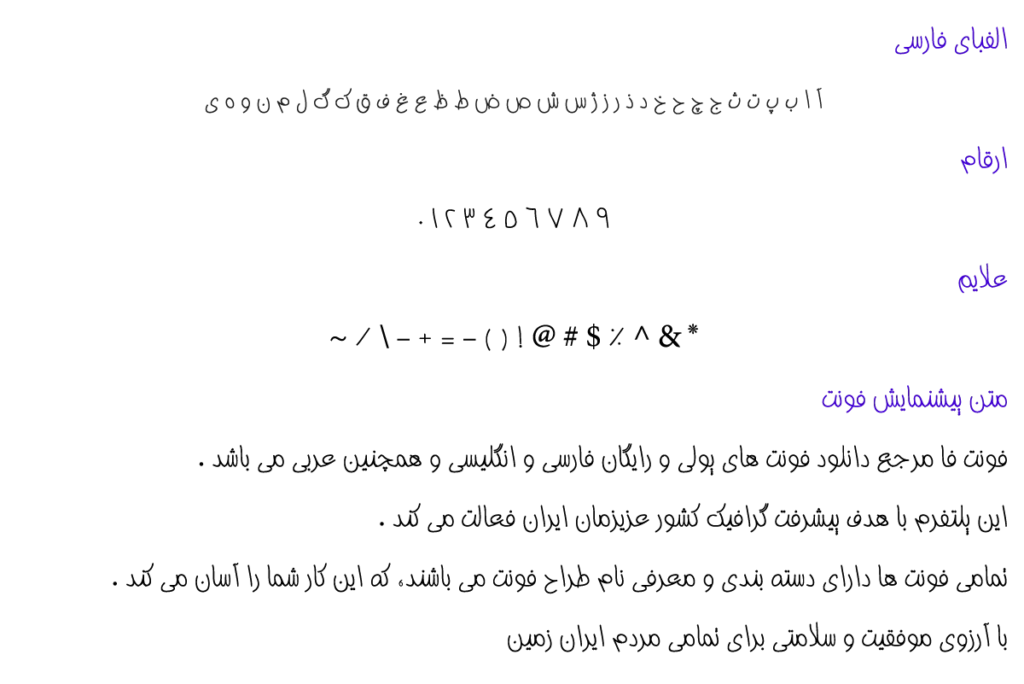
فونت فارسی زیبا – Far Ziba
مجموعه فونت: فونت سری Far
طراح فونت: ابوالفضل سيل سپور نوع فونت: فونت دست نویس
پیشنمایش فونت زیبا
توضیحات و معرفی فونت زیبا
فونت فارسی زیبا ( Far Ziba ) از مجموعه فونت های سری Far می باشد، و نیز نوع فونت دست نویس می باشد.
فونت خوشگل مربوط توسط ابوالفضل سيل سپور در سال 1390 طراحی و ساخته شده است.
و نیز فونت در یک وزن معمولی است.
- Far Ziba Regular
در تصویر زیر میتوانید دموی تایپ فیس مورد نظر را تماشا کنید…